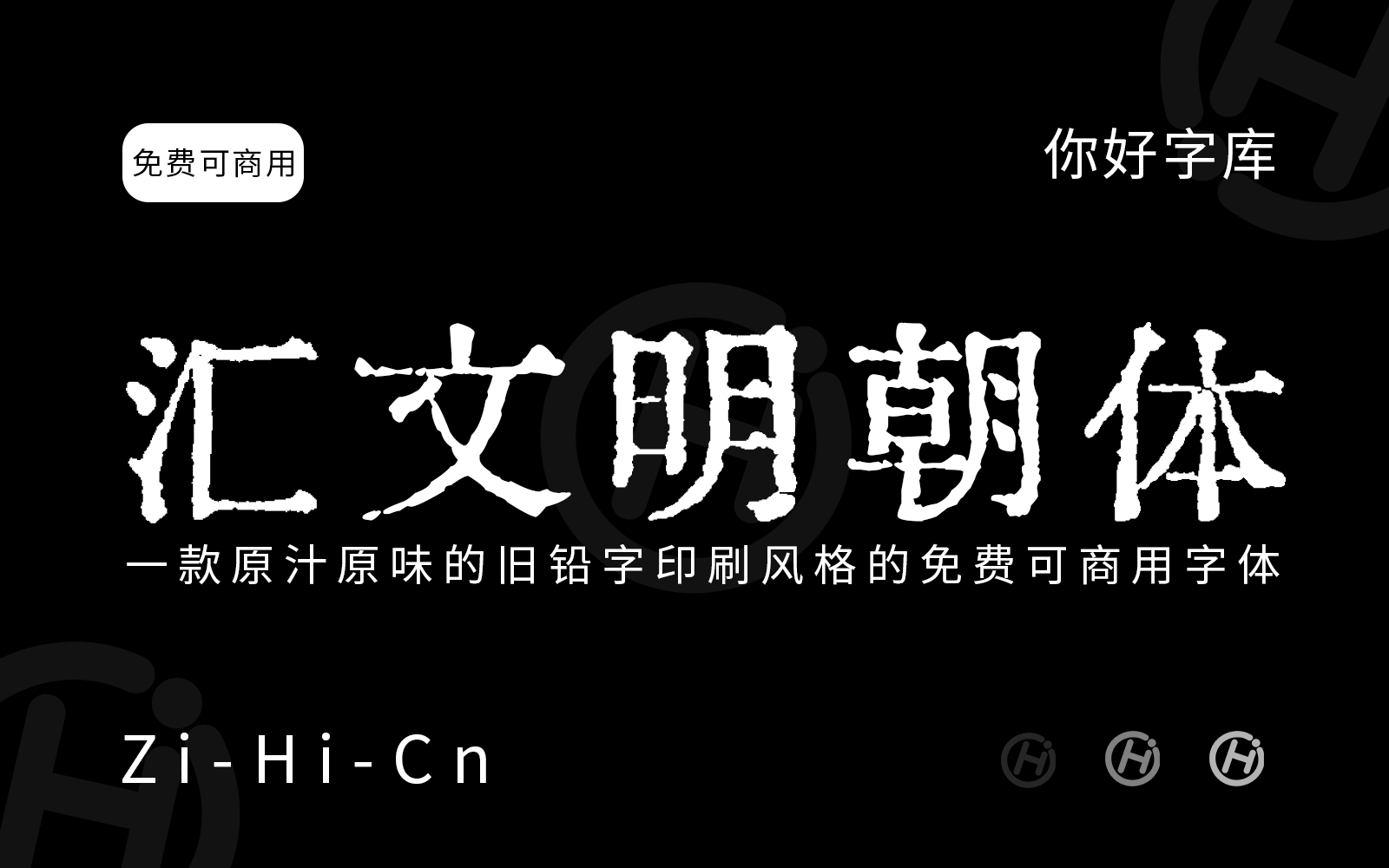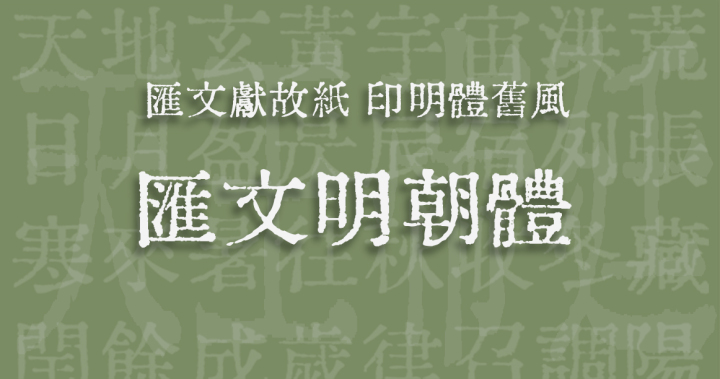
汇文明朝体
字体简介
“汇文明朝体”是一款由百度旧字形吧网友“天王帝廷”创作的免费中文字体,始于2019年1月,最新版本为GBK字符集(2021年更新)。它属于衬线风格,基于1950-60年代汉字改革文件和历史文献(如《文汇报》汉字简化方案草案),还原了简体字在简化后、字形改造前的书籍印刷体样貌,繁体字和传承字则复刻民国至共和国初期的字形,呈现原汁原味的旧铅字印刷风格。